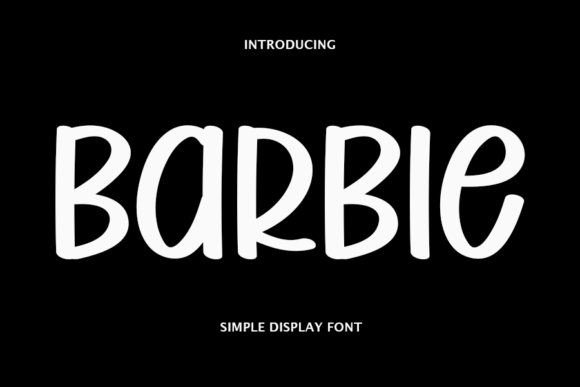
أضف لمسة من الأناقة والأنوثة إلى تصميماتك مع Barbie Font، الخط المستوحى من الأجواء الساحرة والمرحة لعالم باربي. يتميز هذا الخط بحروفه الأنيقة والمنحنية التي تضفي لمسة من الجمال والتميز على أي مشروع.
✨ مميزات الخط:
✅ تصميم أنيق وعصري يناسب مختلف الاستخدامات
✅ مثالي لتصميمات العلامات التجارية، الدعوات، الأغلفة، ومنشورات السوشيال ميديا
✅ جودة عالية لضمان وضوح ودقة في كل تصميم